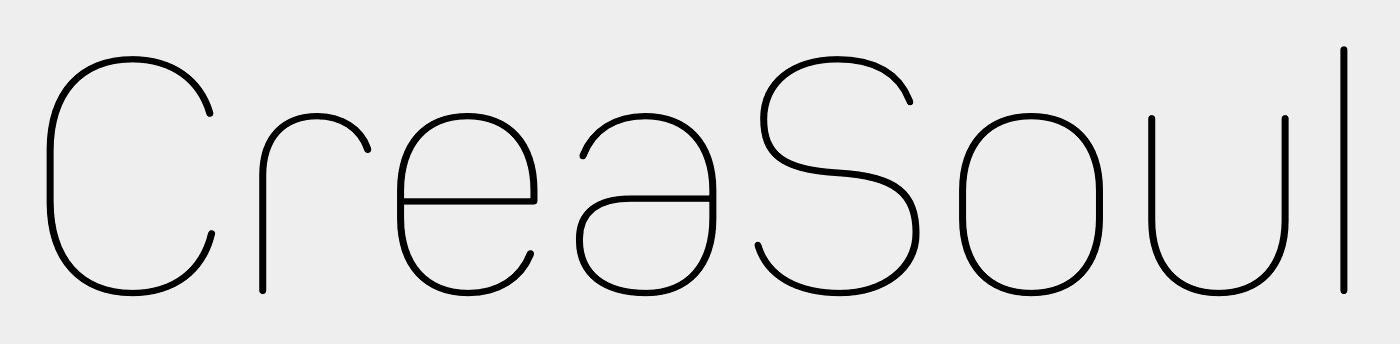
WhatFontIs schlägt Laski Sans vor.
Ich habe aber auch nur nach C, S, o und l gesucht, da ich denke, dass r, e, a, und u gebastelt sind ...
hey super, vielen dank! dachte mir auch, dass da auch abgeändert wurde, e = umgedrehtes a,... und danke auch für deine willkommengrüße! :)
Mir kommt die Schrift sehr bekannt vor. Ich meine, die gibt es so.
Vielleicht erfahren wir mehr im e=a-Strang, welchen ich allerdings nicht mehr finde? :-?
Das e und a hab ich in dieser extremen Form noch nicht gesehen … eher so:
Und beim C, S, o und u dachte ich spontan an die FF Clan:
Stimmt, Clan war’s, was mir die ganze Zeit im Kopf umher ging, kam nur nicht auf den Namen :oops:
Würde mich wundern, wenn das e oder a so in einer Schrift ist, beide sind doch total unausgeglichen und kippeln ...
Die Gestalterin des Logos schweigt seit 2013 auf die Frage, welcher Font verwendet wurde …
ff clan - yes, wenn man den kurzen strich nach unten wegläßt... thx!